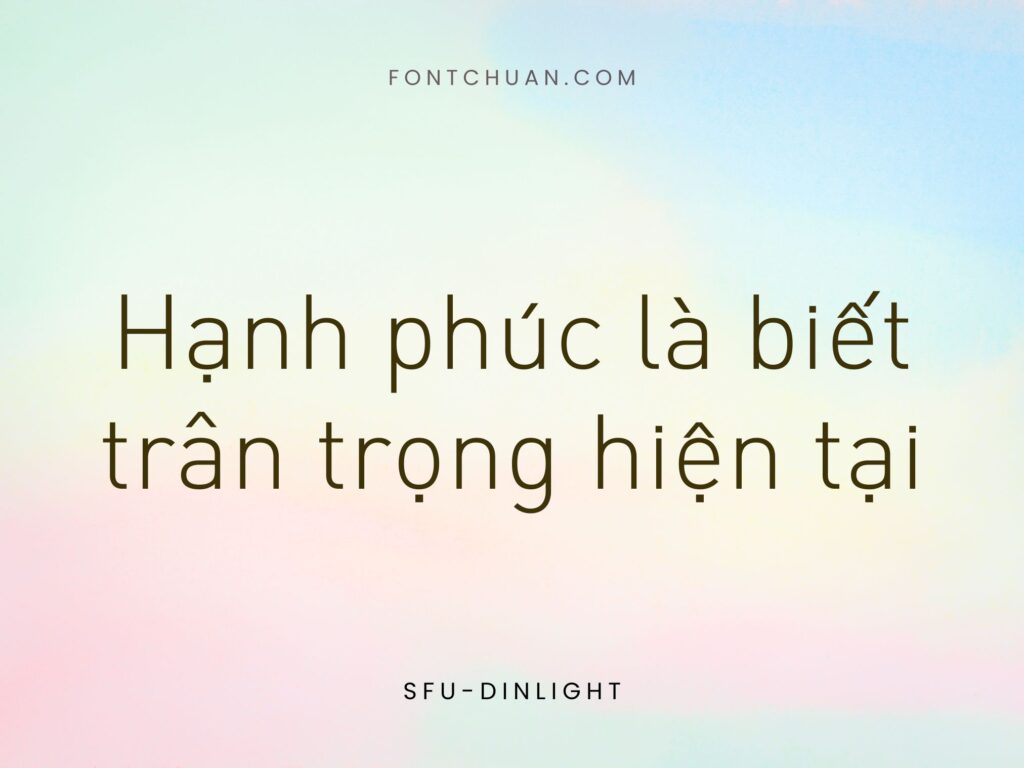
DIN là một kiểu chữ sans-serif mang phong cách công nghiệp, được thiết kế bởi Albert-Jan Pool vào năm 1995, dựa trên DIN-Mittelschrift và DIN-Engschrift theo tiêu chuẩn DIN 1451 của Đức. Tên gọi “DIN” là viết tắt của Deutsches Institut für Normung (Viện Tiêu chuẩn Đức). Ban đầu, DIN 1451 được giới thiệu vào năm 1936, nổi bật với sự đơn giản hình học và tính rõ ràng cao. Sau này, FF DIN – phiên bản thương mại hóa bởi Albert-Jan Pool – đã mở rộng bộ ký tự và thêm nhiều trọng lượng chữ, giúp nó trở thành một trong những font chữ phổ biến nhất.
Mỗi Font sẽ có Font gốc, và Font được việt hóa. Font Chuẩn không phải là người việt hóa, cũng không có các thành viên việt hóa. Font này chỉ được sưu tầm và đăng bởi thành viên của Font Chuẩn. Về mặt thiết kế, DIN mang đến cảm giác hiện đại, tối giản và chuyên nghiệp, với đường nét gọn gàng, cân đối, độ tương phản thấp, dễ đọc trên cả màn hình lẫn in ấn. Font này phù hợp với nhiều ứng dụng như thiết kế bao bì, logo, thiết kế web và được sử dụng phổ biến trong quảng cáo, bất động sản, công nghệ, giáo dục.